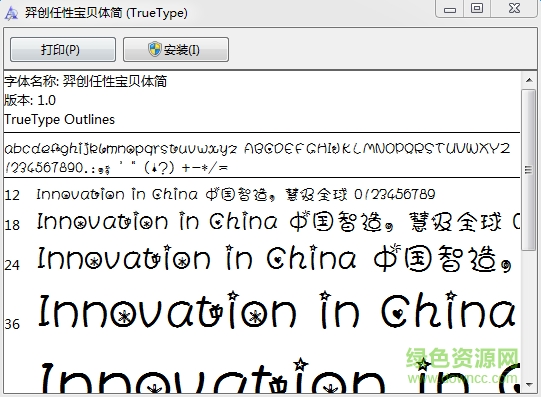
羿創(chuàng)任性寶貝是一款很有特色的電腦字,這種字體寫出來的字是很好看的,不像普通的字體那樣是很呆板的,它比較活潑,而且字體上還有各種裝飾物,這種具有藝術(shù)風(fēng)格的字體用于藝術(shù)設(shè)計(jì)方面是很不錯(cuò)的,歡迎有需要的朋友來綠色資源網(wǎng)下載。